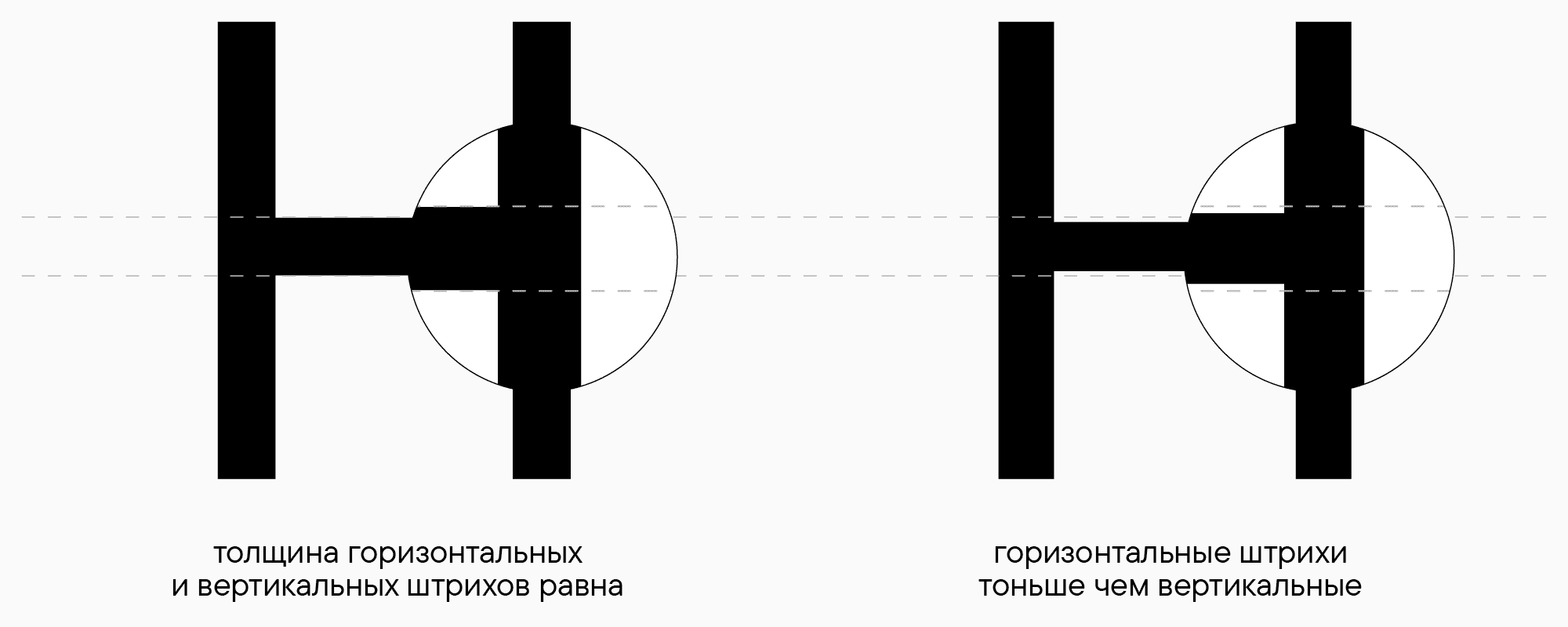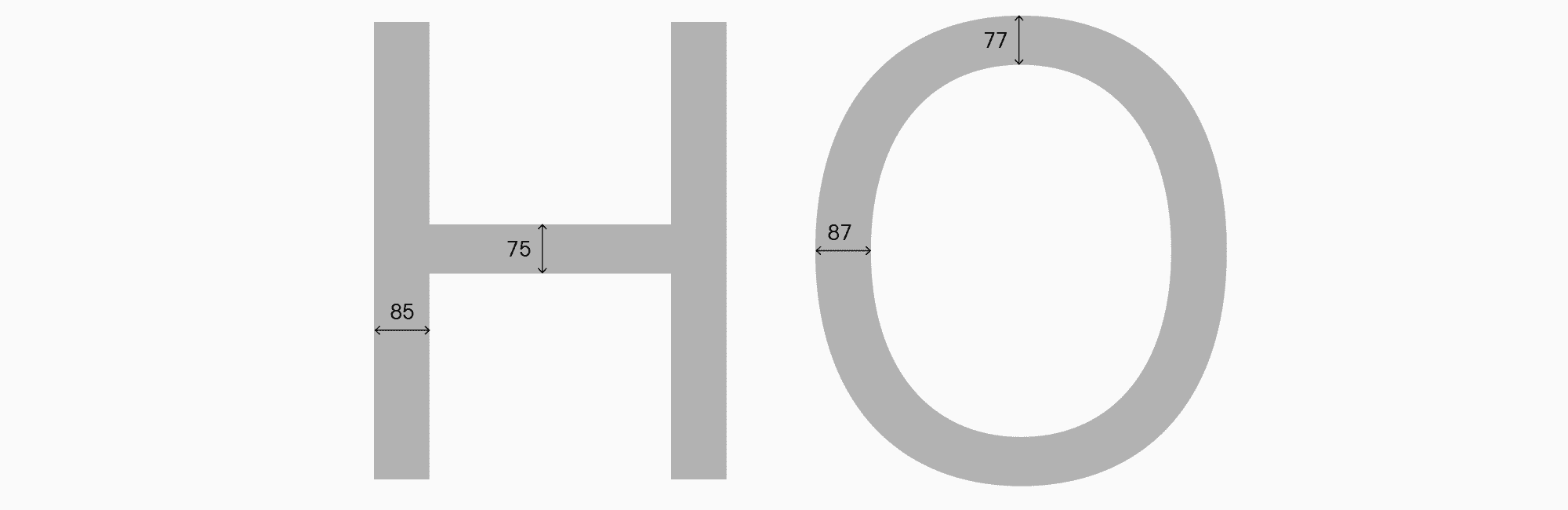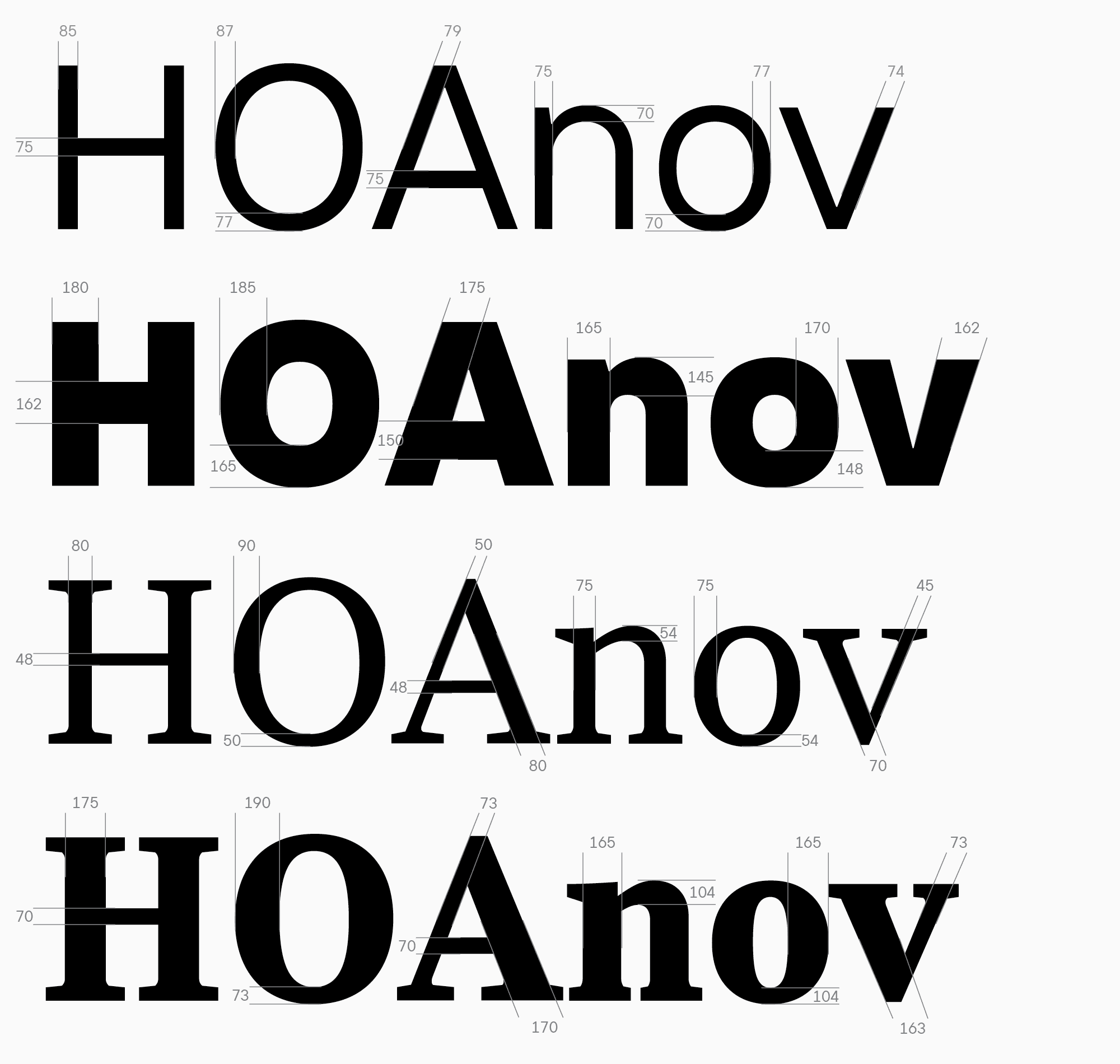
Продолжаем наше увлекательное погружение в многогранную тему шрифтового дизайна! Напоминаем, что мы рассказываем о процессе создания шрифтов поэтапно, поэтому перед чтением этой статьи рекомендуем ознакомиться с предыдущими материалами из цикла «УниверситеТТ».
На этот раз мы поговорим о первом этапе отрисовки базовой латиницы — построении знаков, определении всех графических особенностей, пропорций, консистентности. А расскажет обо всем этом дизайн-лид TypeType Антонина Жулькова. Тоня занимается шрифтовым дизайном уже более 5 лет. Она — автор идей и главный дизайнер в таких проектах, как TT Neoris, TT Ricordi Allegria, TT Globs, Ivi Sans Display. Также принимала участие в создании шрифтов TT Fellows, TT Fors, TT Interphases Pro, TT Commons, Red Collar и многих других. Вы могли слышать Тонины лекции и выступления, в частности — на «Дизайн-выходных».
С чего начинать рисование базовой латиницы?
После того, как вы провели всю подготовительную работу, определились с задачей и основными характеристиками шрифта, а также сделали скетчи, самое время перейти к отрисовке знаков в шрифтовом редакторе.
Основная идея, которую я хочу донести в этом разделе, заключается в том, что шрифт — это не отдельные буквы и символы, а единая система. Поэтому любое графическое решение может и должно влиять на все остальные знаки. С одной стороны, эта концепция может показаться очень ограничивающей и неинтересной. Но, с другой, именно консистентность шрифта помогает нам как с графической точки зрения, соединяя все знаки воедино, так и в процессе работы. Понимание базовых принципов построения шрифта облегчает выстраивание всего процесса отрисовки. Повторю еще раз: понятная логика построения — это лейтмотив всего процесса рисования знаков шрифта и главенствующий фактор при принятии решений.
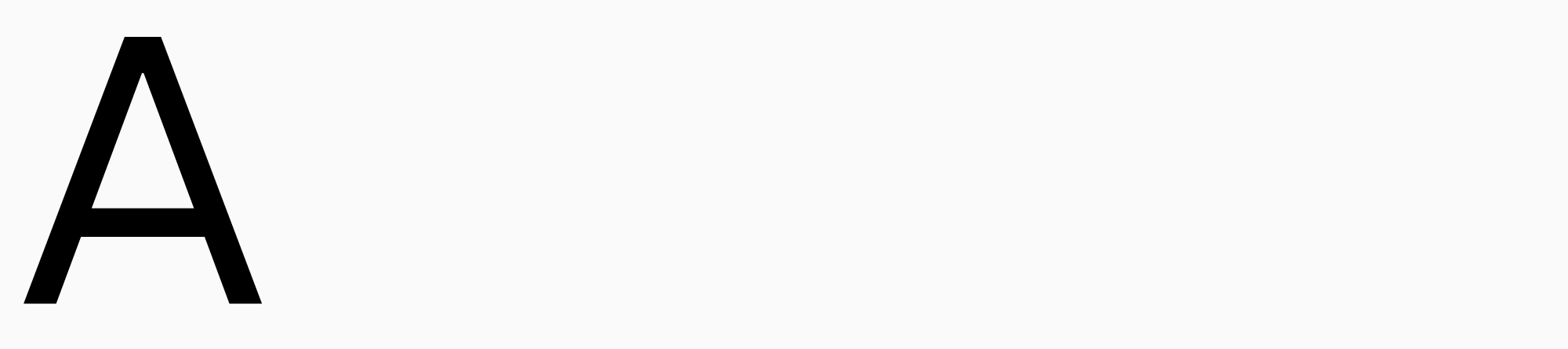
Отрисовка любого шрифта в редакторе начинается с проектирования основных знаков латиницы в двух регистрах (прописные и строчные). Именно с их помощью мы уточняем для себя толщины и пропорции, на которые будем опираться при рисовании всех остальных знаков. Рисовать эти буквы нужно на основе уже готовых скетчей.
В качестве примеров я покажу два шрифта — антикву и гротеск, чтобы вы могли сравнить два основных стиля и понять, как отличаются и в чем сходятся процессы работы над ними.
Мы будем рисовать шрифт, опираясь на уже знакомые нам из предыдущих «уроков» задачи — создание современной функциональной антиквы и нео-гротеска для интерфейсов. В некоторых случаях будут встречаться и примеры из других шрифтов, чтобы вы увидели полную картину описываемых процессов. Сразу обозначу, что пока мы будем обсуждать только прямые начертания. Путешествие в мир италиков будет ждать вас в следующих главах.
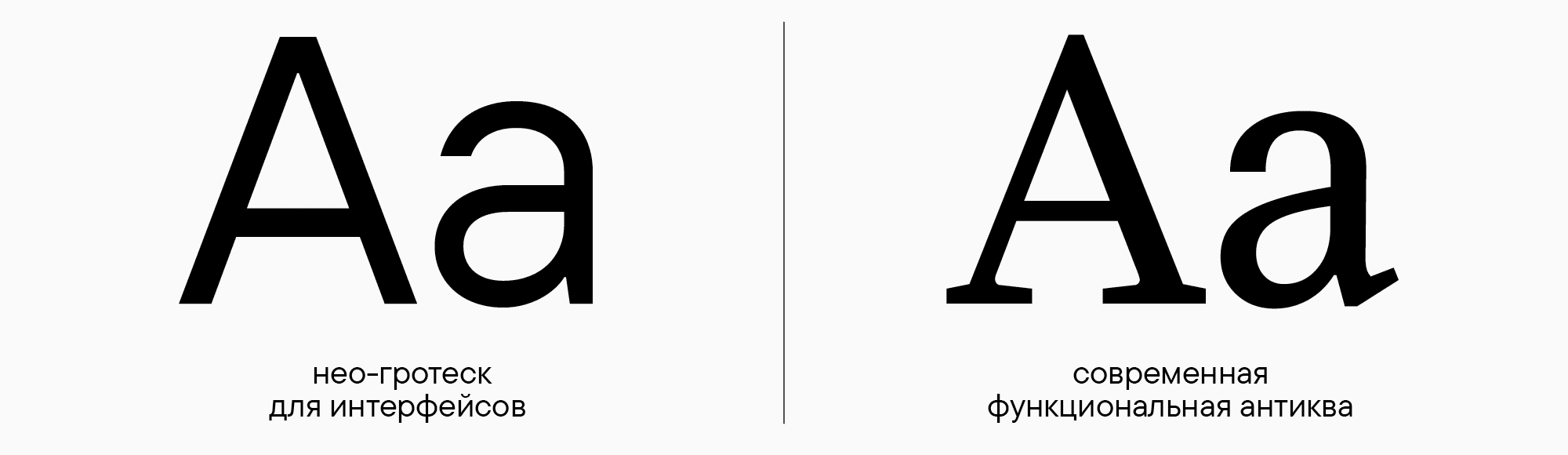
Начало работы: первые знаки
Все буквы базовой латиницы можно условно поделить на три группы знаков: прямые или прямоугольные (например, «Н» или «n») , круглые («О»,»o«) и треугольные («А» или «v»). Именно с них начинается наша работа, и на их основе мы будем строить все остальные буквы.
Свой рассказ про рисование знаков я начну с прописных букв. На это есть две причины. Во-первых, исторически в латинской письменности прописные знаки появились раньше, чем строчные. Во-вторых, логика построения этих знаков немного проще, чем у строчных букв. Если вы делали только скетчи строчных букв, то на этом этапе можно вернуться к эскизам и нарисовать буквы «Н», «О», и «А» рядом с ними, чтобы определиться с пропорциями и толщинами и понять, как строчные знаки в вашем шрифте соотносятся с прописными. Конечно, вы можете начинать с рисования букв в любом регистре, чтобы проработать графическую идею. Но мне кажется, что начинать рассказ с прописных букв методологически правильно.
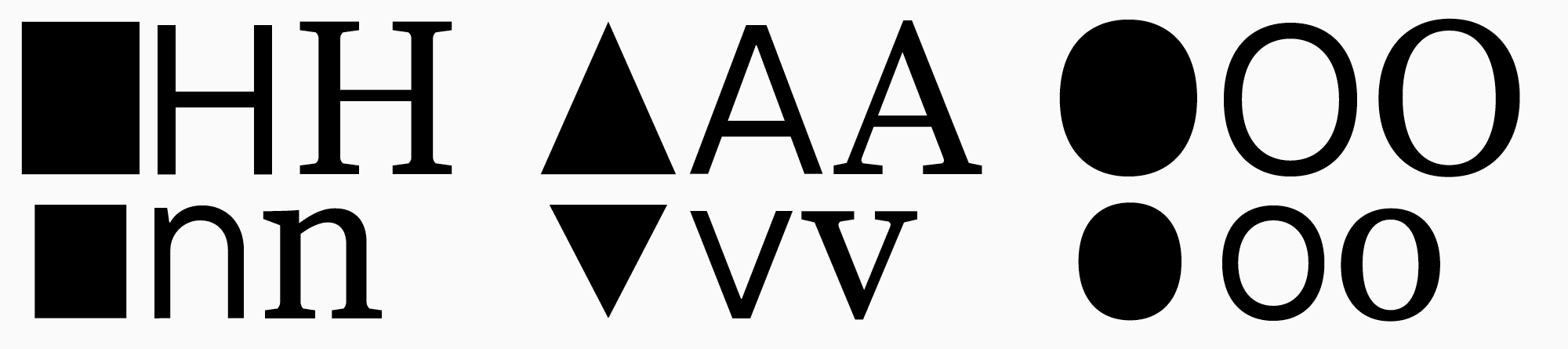
Если вы планируете рисовать целое шрифтовое семейство со множеством весов, то следует начинать с «регулярного» начертания, которое вы решили сделать «мастером» на этапе скетчинга. Это правило работает в относительно нейтральных шрифтах, в которых важна читабельность и логика построения знаков. Кроме того, в регулярном начертании проще разобраться со всеми графическими характеристиками. А вот рисование акцидентных шрифтов может ограничиваться только вашей фантазией, выбор мастера здесь не играет большой роли. Подробнее о нюансах планирования шрифтового семейства мы рассказывали в статье «УниверситеТТ: Урок 4».
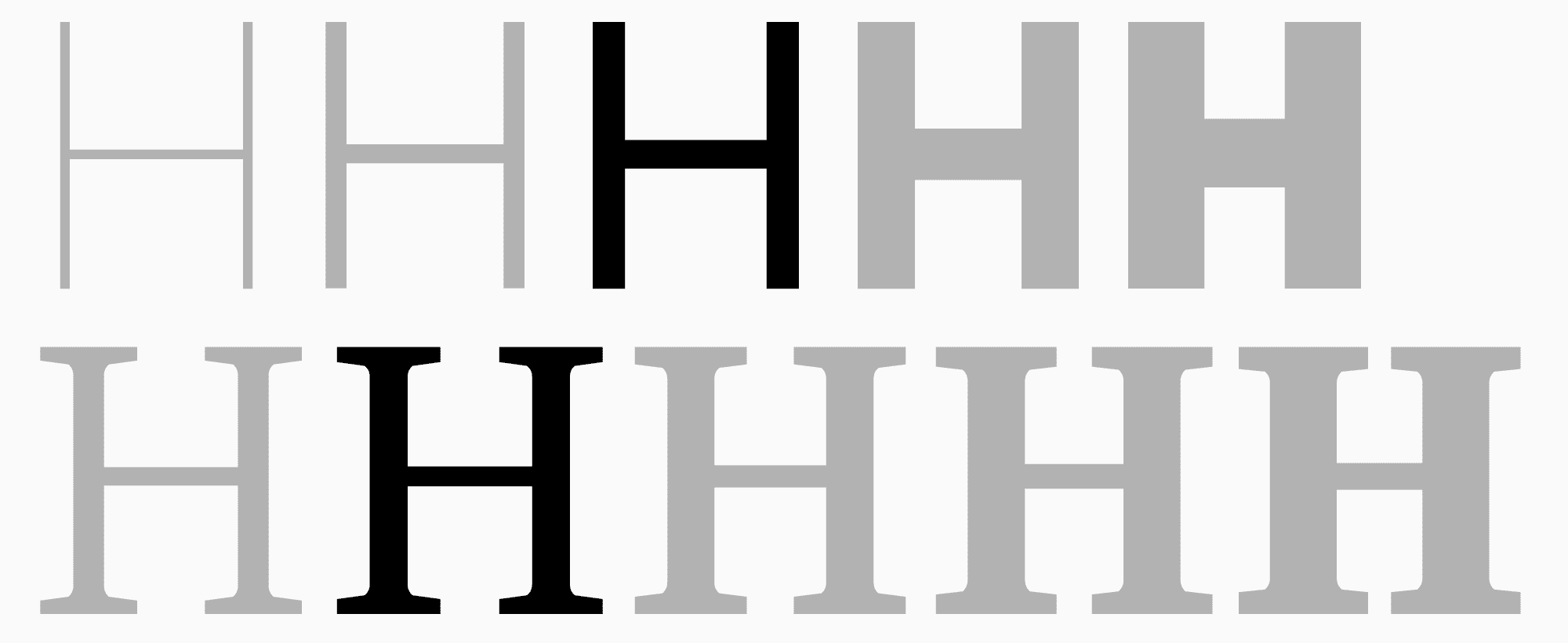
Параметры толщин в знаках и оптические компенсации
До того, как мы перейдем непосредственно к рисунку, нам нужно обсудить теоретический блок про разнообразные толщины знаков в шрифте. Числовые параметры толщин очень важны для проектирования шрифтов. Во-первых, именно на них мы будем опираться при построении всех остальных знаков в шрифтовом семействе. Во-вторых, с их помощью мы можем идентифицировать любой шрифт и определить, к какой стилистической классификации он относится и подходит ли для выбранной задачи.
Особенности нашего зрения таковы, что «математически верные» фигуры одного размера, расположенные рядом, не кажутся нам одинаковыми. Для шрифтового дизайнера это очень важный момент. При рисовании букв нужно учитывать этот аспект восприятия, чтобы набор текста выглядел равномерным и ровно стоял на строке. Лучше всего это видно на примере геометрических фигур.
На верхнем рисунке круг выглядит меньше, чем прямоугольник, а треугольник — еще меньше, чем круг. При этом на самом деле высоты всех фигур идентичны. А на втором рисунке фигуры скомпенсированы с учетом визуального восприятия, поэтому выглядят одинаковыми по высоте. Фактически же круг и вершина треугольника выходят за границы «базовых» линий. Вы можете провести такой же эксперимент (в графическом редакторе или на листе бумаги) с разными типами фигур и с разными их характеристиками, чтобы самостоятельно почувствовать разницу восприятия.
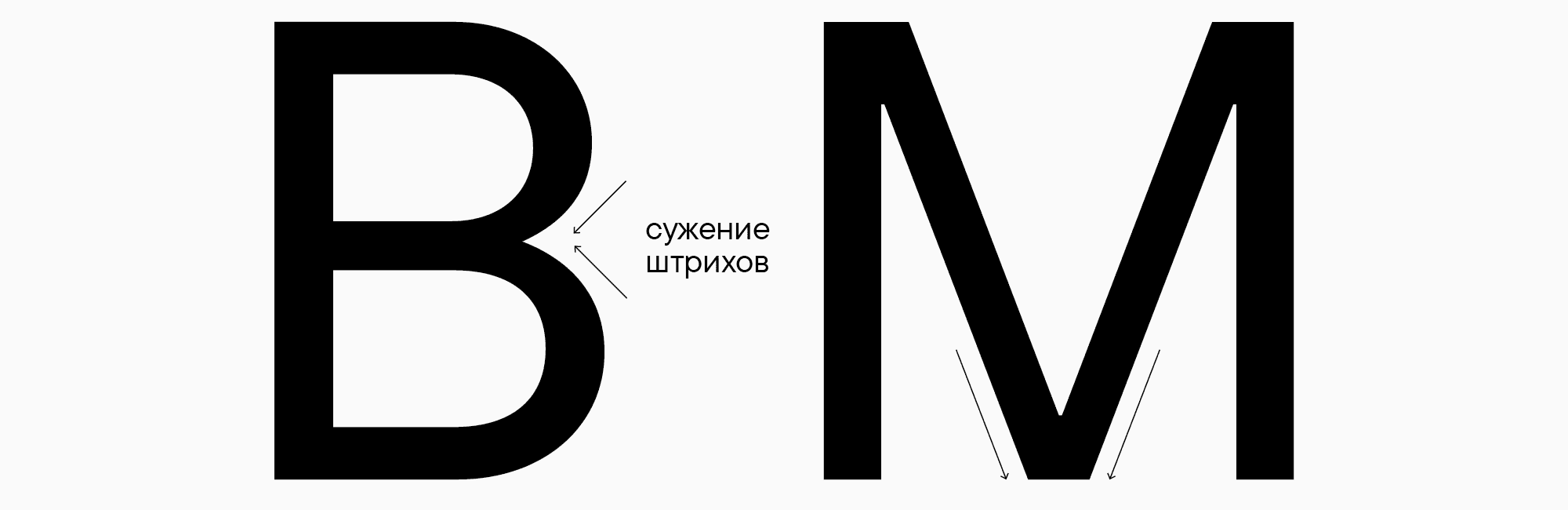
В следующей статье мы продолжим говорить об оптических компенсациях и поймем, как определиться с высотами прописных и строчных знаков, а также разберемся с понятием контраста.